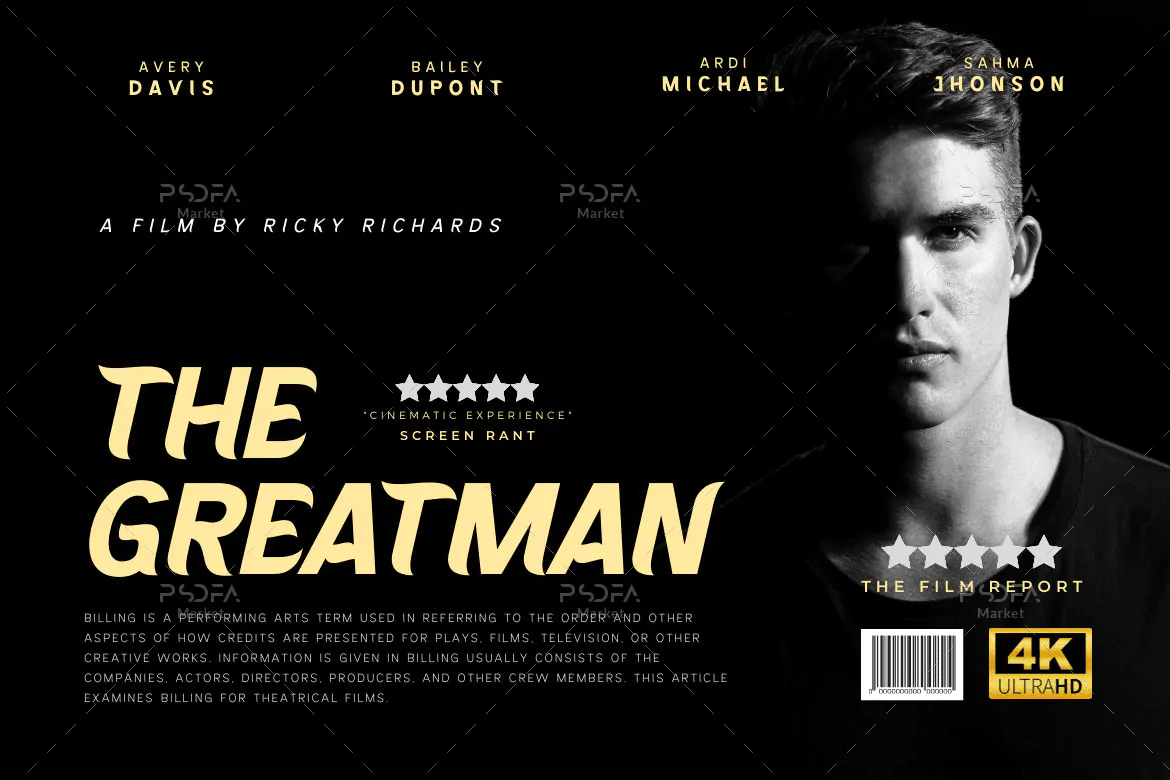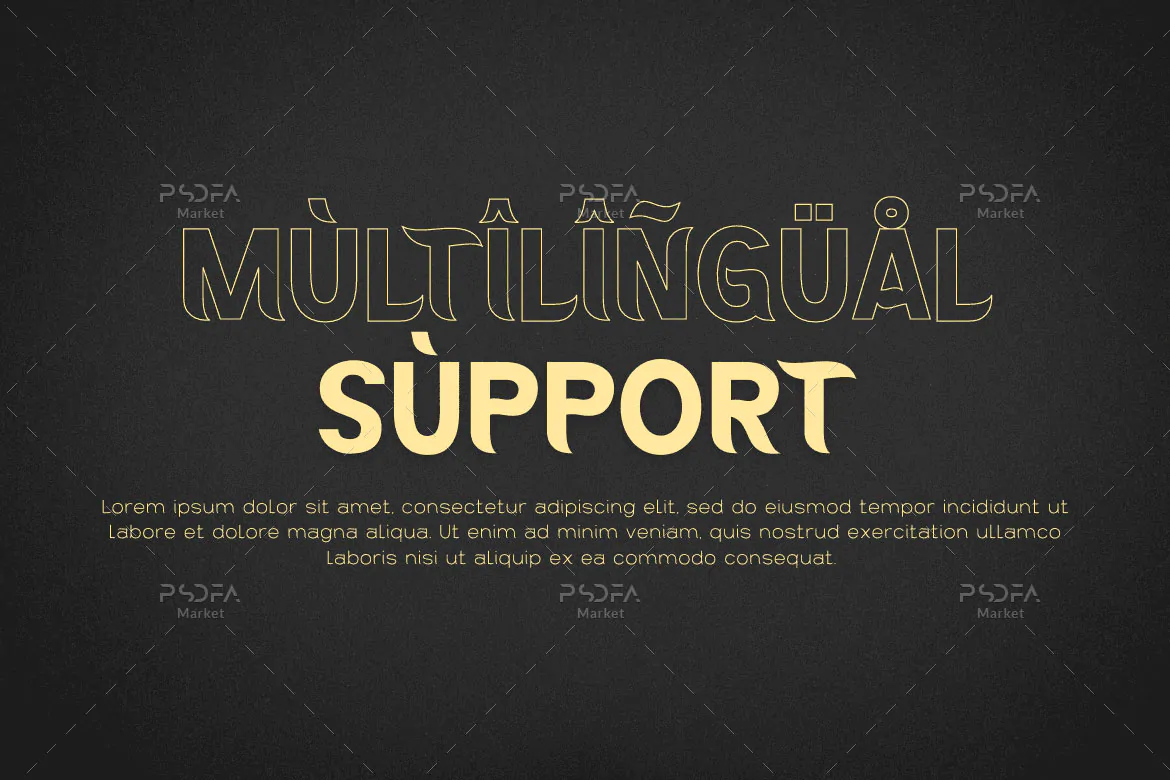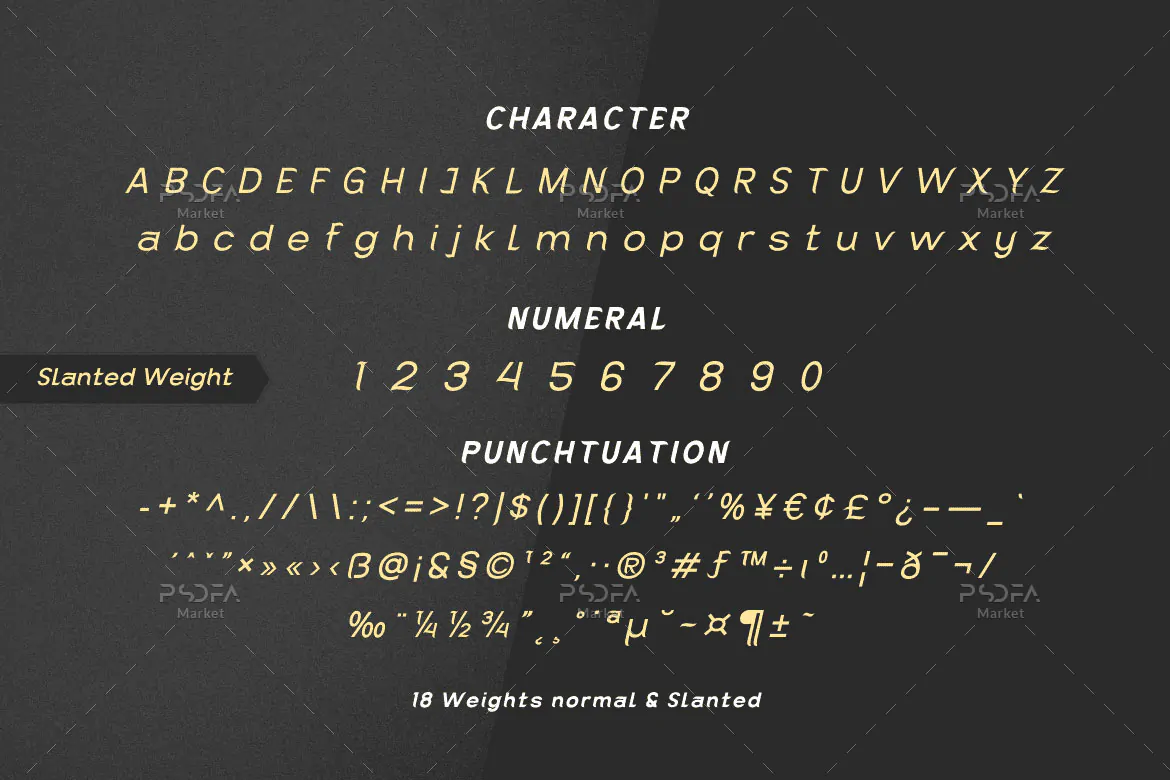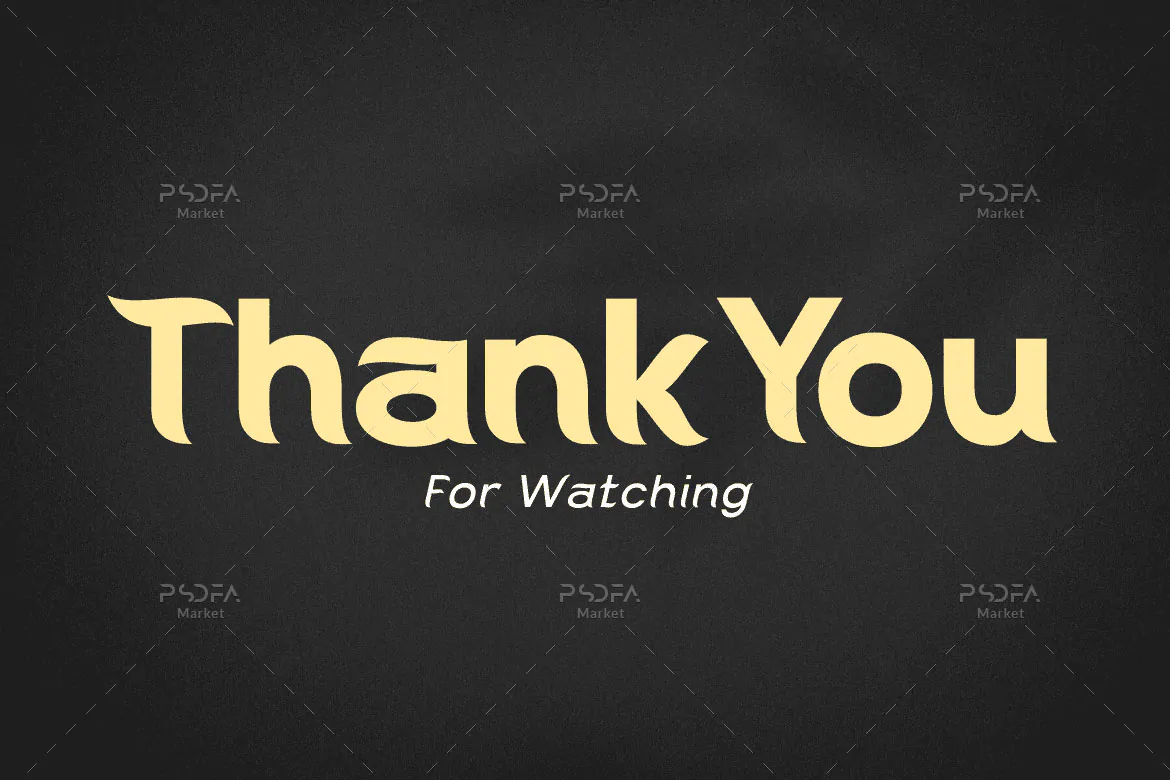
فونت سنس سریف مدرن Kajju
فونت سنس سریف مدرن
فونت سنس سریف مدرن Kajju یک قلم انگلیسی زیبا است که مناسب جهت استفاده در طرح و پروژههای گرافیکی مختلف میباشد. فونت Kajju با 15 وزن مختلف طراحی شده است که میتوانید از آن در طراحی انواع پوستر، کارت ویزیت، بروشور، تراکت، بنر، تقویم، بسته بندی محصولات، لوازم التحریر و … استفاده کنید.
- Thin، Light، Regular، Medium، Italic، Bold، Black